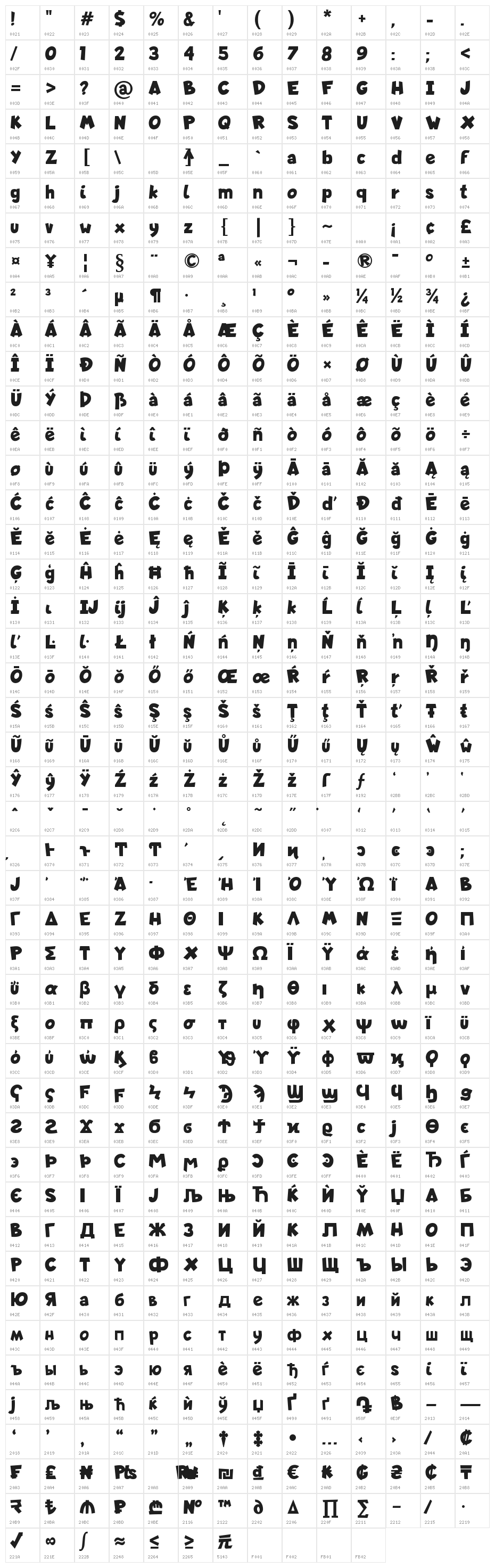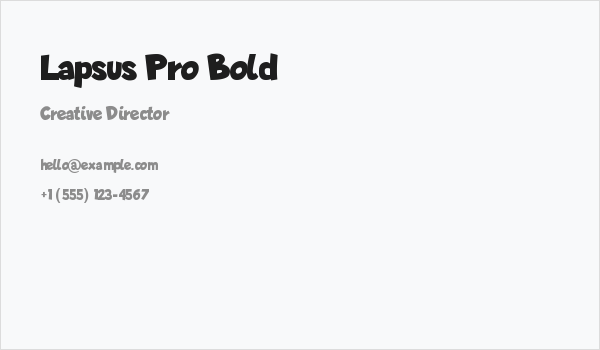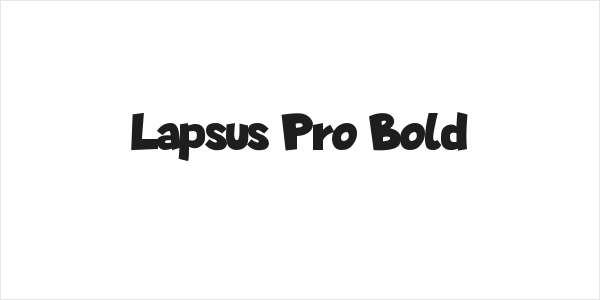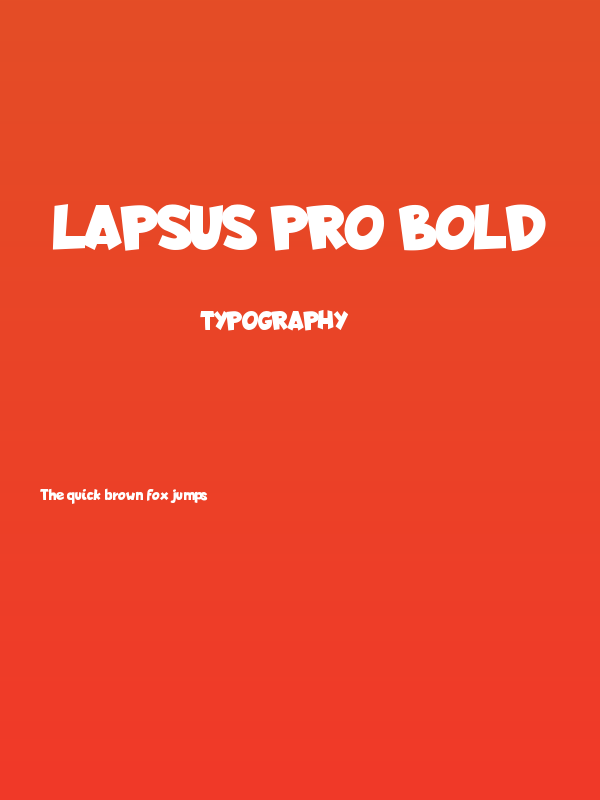
Lapsus Pro Bold Font
| Stil general | Playful, Energetic |
| Caz de utilizare | Headlines, Posters, Branding |
| Proiecte propuse | Ideal for children's books, comic strips, playful branding, and event posters. |